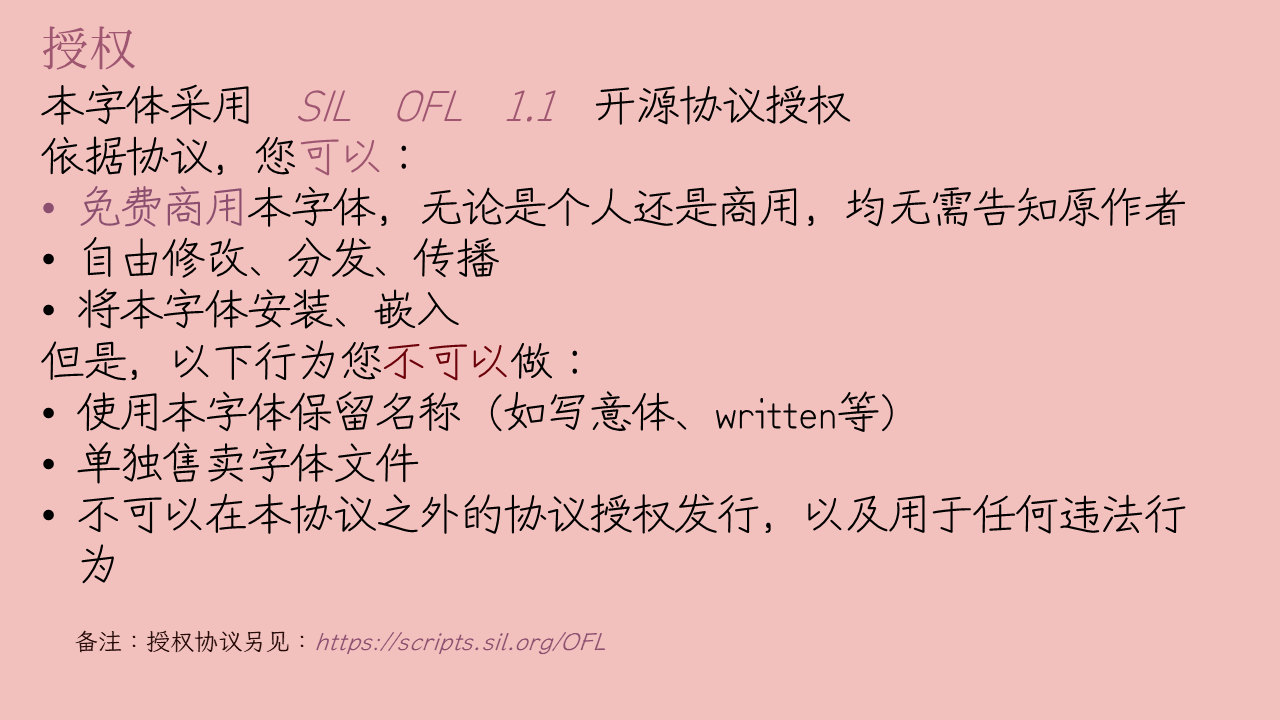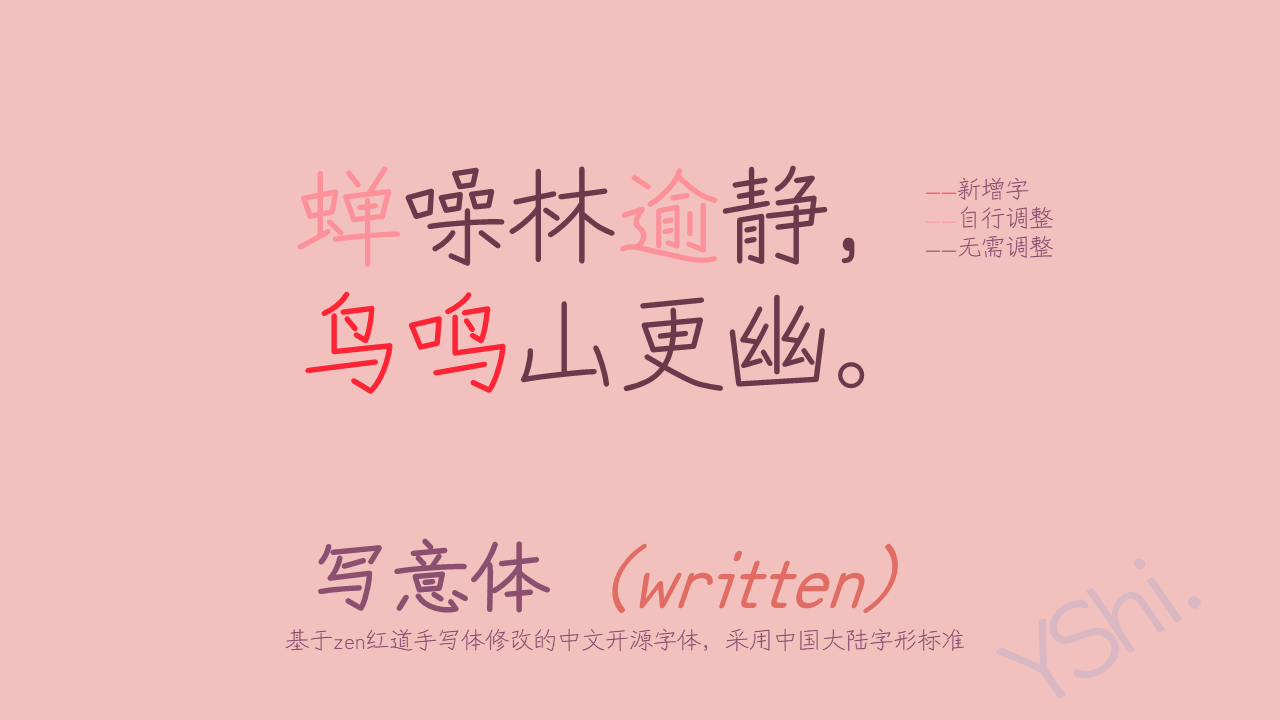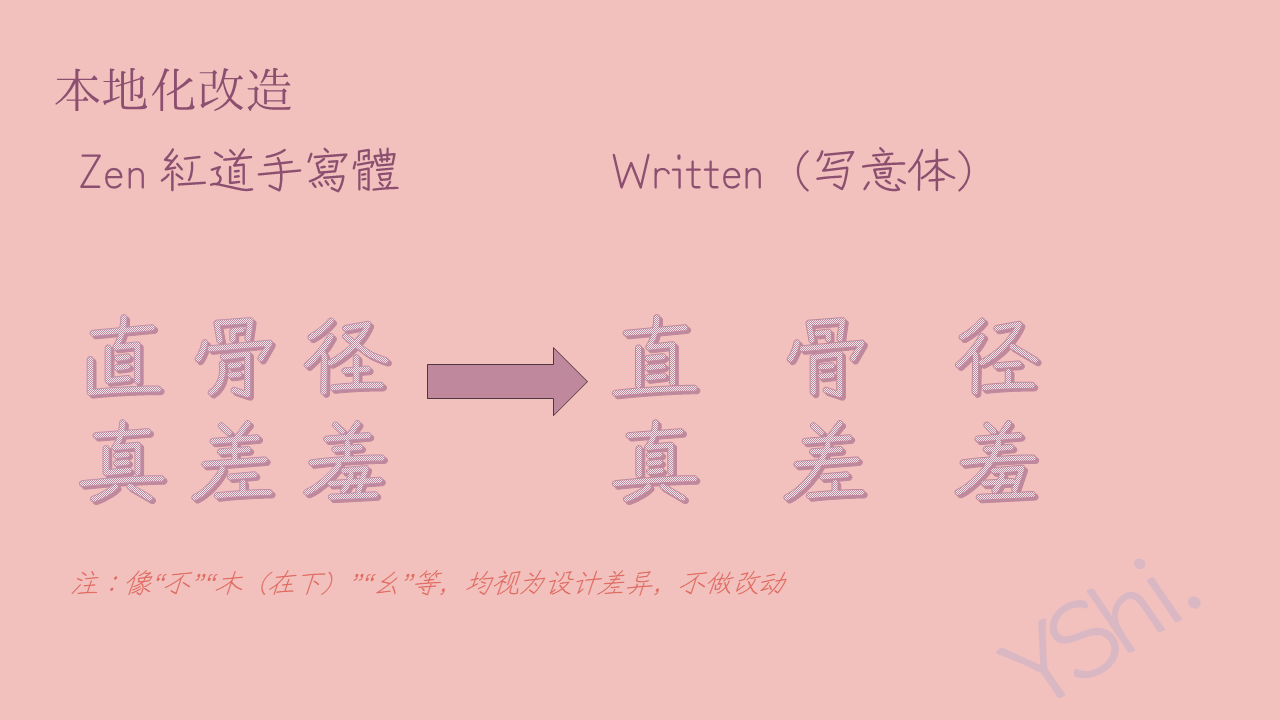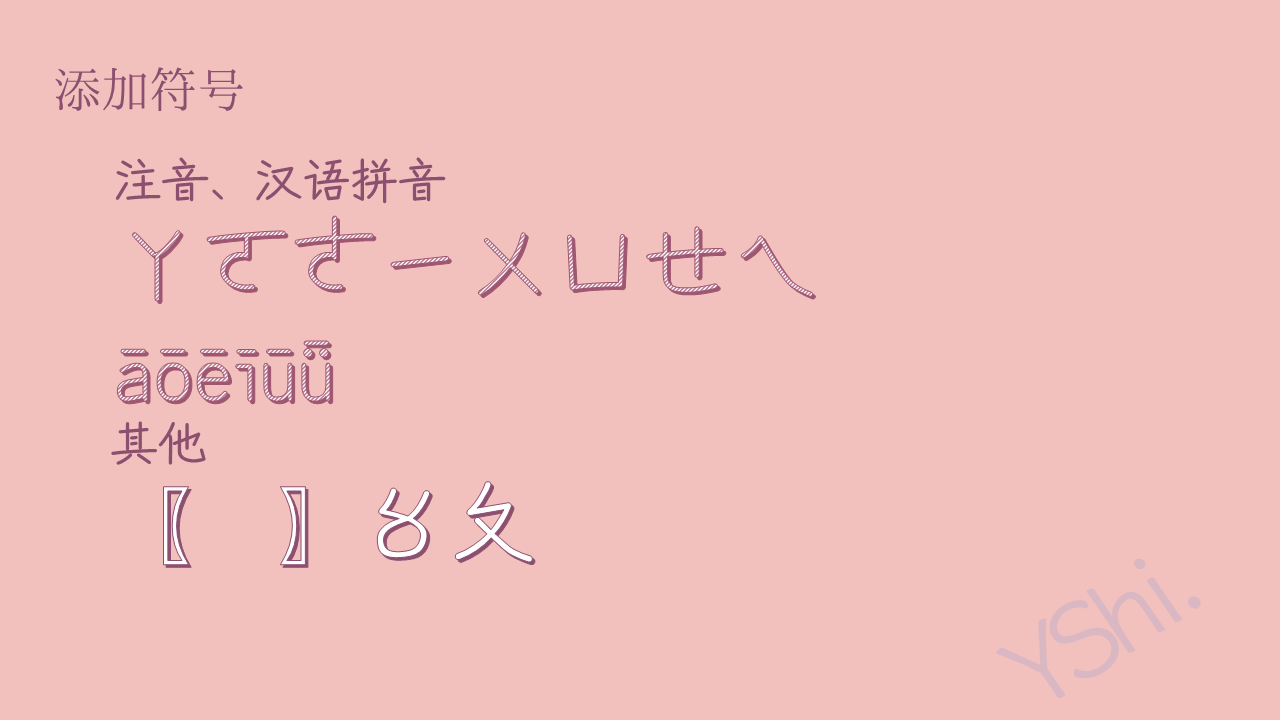
写意体
别称:YShi-Written
概述
YShi-Written / 写意体
一款开源中文字体,基于 Zen 红道手写体改,参照中国大陆字形标准。
由于该字体有一种由中性笔书写出来的特性,故起名 “Written”;中文名为 “写意体”,源于他人建议。但是字体字数不足以满足简体中文显示,故创建此工程,补简体并且改 G。